人民币上的字体你了解吗
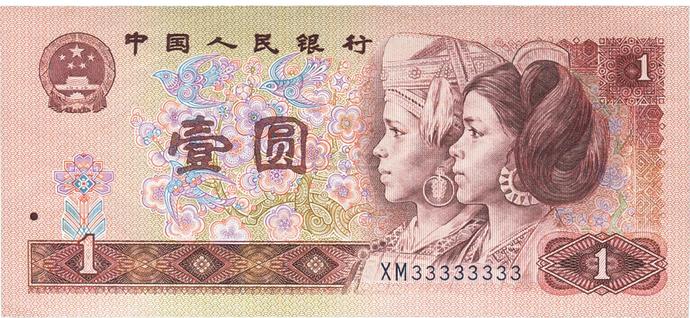
我们每天都在接触人民币,可人民币上“中国人民银行”这几个字从书法角度它用的是什么字体呢?现在小编就给你展示一下,见识见识。
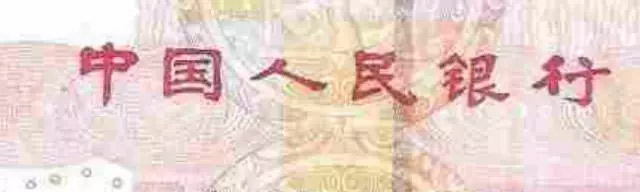
这六个字出自马文蔚先生之手。马文蔚先生是山西省太原市阳曲县黃寨村人,生于一九零四年。他性格刚毅,博学多才,尤善书法。他的字体为“张黑女”碑体,它是北魏碑体的故名,被认为是北魏碑体中的精品。此书体苍劲端庄,独具匠心,自成一体,实为人民币增色不少。
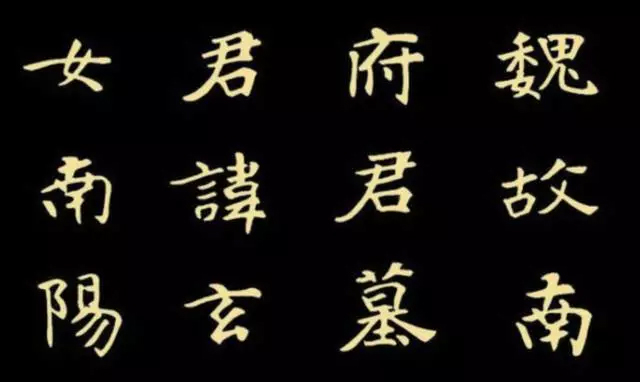
原来人民币上“中国人民银行”这几个字属于“张黑女”,这个张黑女,读作张(zhāng)黑(hè)女(rǔ),音(张贺汝),是书法的一种碑体。这种字体首次出现在《张黑女墓志》上,《张黑女墓志》全称为《魏故南阳太守张玄墓志》,又称《张玄墓志》。此碑成于北魏普泰元年原石已佚,现仅存清何子贞旧藏拓本。清书法家何子贞评之曰:“化篆分入楷,遂尔无种不妙,无妙不臻,然遒厚精古,未有可比肩者”。
此志楷书二十行,每行二十字,共三百六十七字。其书法精美遒古,峻宕朴茂,结构扁方疏朗,内紧外松,多出隶意。此墓志虽属正书,行笔却不拘一格,风骨内敛,自然高雅。笔法中锋与侧锋兼用,方圆兼施,以求刚柔相济,生动飘逸之风格,堪称北魏书法之精品。
《张黑女墓志》基本点画图解
“点”
《太》瓜子点
笔锋逆向入纸,落笔后向右下运行,笔毫圆满铺开,然后提笔调锋,使笔锋从点画中作收。此点势侧,体丰满。
《方》平点
藏锋落笔后,笔锋向右,横向铺毫,回锋轻收,笔势还原,从点画中作收,其势横,形体略长。
《盪》圆点
笔锋垂直轻下后,将笔毫向四周铺开,再提笔将笔锋收拢,从点画中央提出作收。
《泰》竖点
藏锋落笔后,笔锋向下方运行,势较直,将笔锋铺开后,提笔向上,回至点画中部收笔。
“横”
《無》横四点
四点并列,第一点单独成点,第二、三点稍轻并有牵丝联系,第四点下笔后向右铺毫,略重再提笔中部腹部收笔。
《一》平横
起笔逆入,横画直下,提笔调锋,向右铺毫中锋运行,收笔圆满向左,回锋向画中。点画中截有起伏提按。
《何》凸横
指《何》可字的第一横。起收笔与平横相同,中间略呈凸出使点画细韧有力。
《誌》横三点
此三点姿态不同,第一点起笔后,向左处行笔再收笔,第二点起笔从左向右行笔,收笔将锋向第三点带出,第三点较厚重,但点的势,亦一点高于一点。
“竖”
《军》垂露竖
逆锋起笔、竖画横下、笔锋提正、中锋行笔、挺拔坚实,回锋向上实收笔。收笔处教圆润,故称垂露。
《行》短竖
用笔的过程同长竖,只是过程缩短,而更显有力。
《坚》向势竖
逆锋起笔,斜横下笔,提笔中行,略向左努出,似弯弓状。短势而有韧劲。
《平》悬针竖
逆锋起笔,下笔后提锋至点画中,中锋行笔,坚韧有力,收笔时笔锋逐渐提起,但不离纸,向上虚势作收,使收笔处锐利,故称悬针。
“挑”
《北》短挑
逆锋起笔,斜下笔,提中后向右上挑去,用力到锋尖,短而锐。
《摧》长挑
起收笔同短挑,中段稍长,用力到锋尖,长而扬。
“撇”
《之》平撇
逆锋起笔,斜下笔后,锋提中,向左下撇出,其势平,连接平捺使字平稳。
《若》弧撇
起笔逆入后,斜下笔,锋提中然后作弯势行笔,至出锋处再作一个弧形出锋,笔力到底。
《风》直撇
此撇似写竖画,其势微左至出锋处,向左撇出,宜直而不僵。
《歼》斜撇
此撇势斜,锋中且劲,至出锋处收笔回锋略向上提。
“折”
“白”横折
先作横画,至转折处提笔横下笔调锋中锋运行直下,转角处有提按,但动作要轻,勿使耸肩。
“既”竖折
先作竖画,至转折处提笔调锋,动作要轻、圆,勿使出现折角,竖折应一笔完成。
“女”左斜折
先斜画,回稀向上提接着再作反捺,在收笔处要将峰调正还原。
“海”右斜折
先作横画,在转角处提笔调锋,然后现向左斜下行钩出。
“钩”
“丁”平钩
先作一竖,应坚韧有力,出钩时笔锋略提向左平推,使钩角满、势平,出锋处圆满。
“守”弧弯钩
逆锋入纸,直画横下,提笔下行渐取弯势,使成弧形,再收笔向左下推出。
“风”背抛钩
先作横,势向右上微斜,转折处提笔调锋,然后向内凹直下,再向外弯,再提笔调锋向右上出钩。有弯度,用笔宜轻重适当。
“殲”戈钩
逆锋横斜下笔,调锋向下中锋运行,轻重徐疾地作弧形,下行至适当处,向右上钩出。
“捺”
“之”平捺
此捺笔势交平,一波三折行笔由轻渐重,至出锋处将笔毫收拢提出,收笔虚回。
“太”斜捺
起笔由左撇而来,稍一驻笔后,铺毫,中锋向右下方由轻而重,顿挫向右捺出,收笔虚回。
“东”短捺
用笔与斜捺相同,中段行笔短而有力。
“雙”弧形捺
起笔轻,行笔取下凹势,呈弧形,铺毫提笔作收。此捺在字的下部托住整个字,使字稳重。